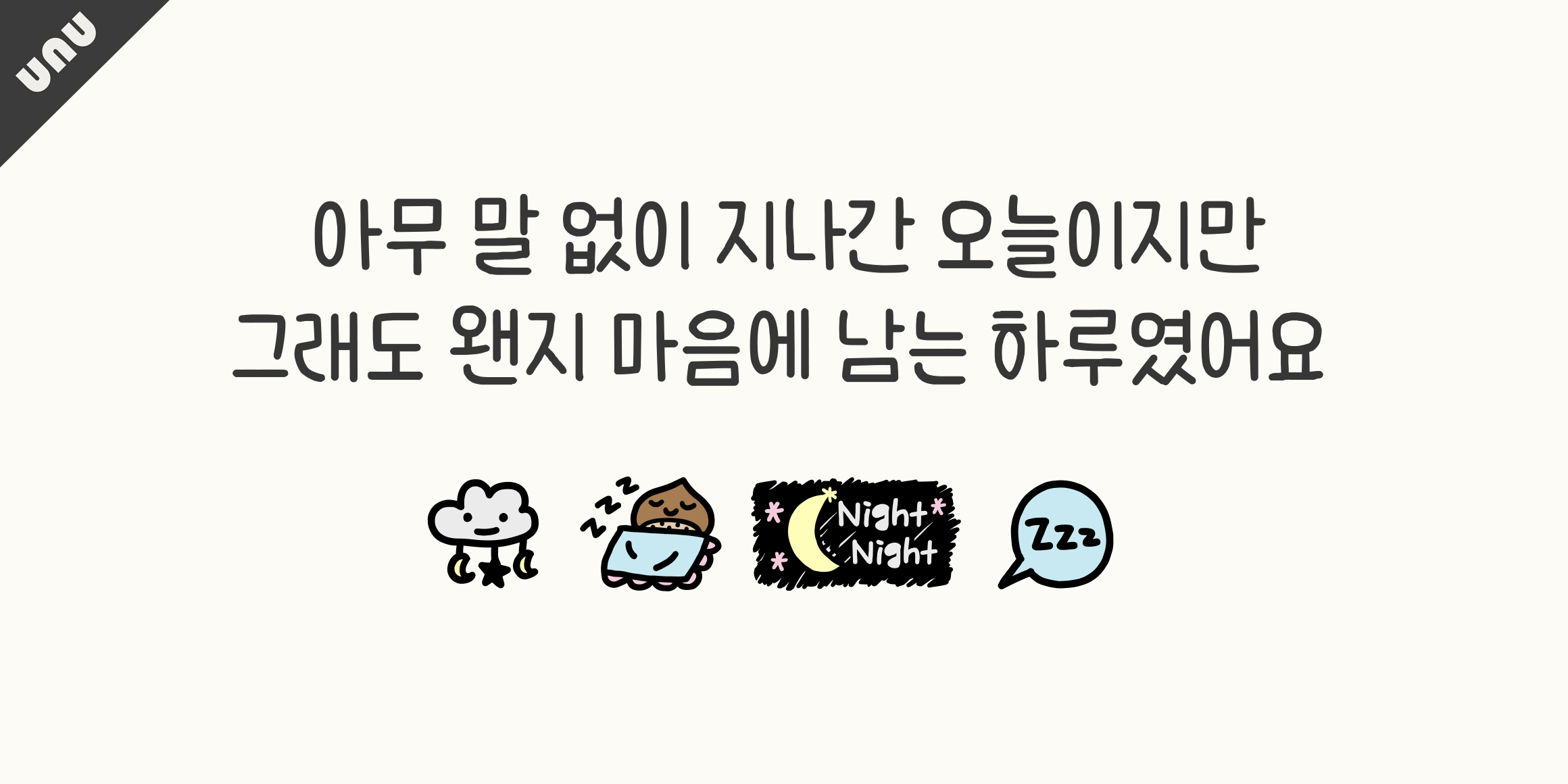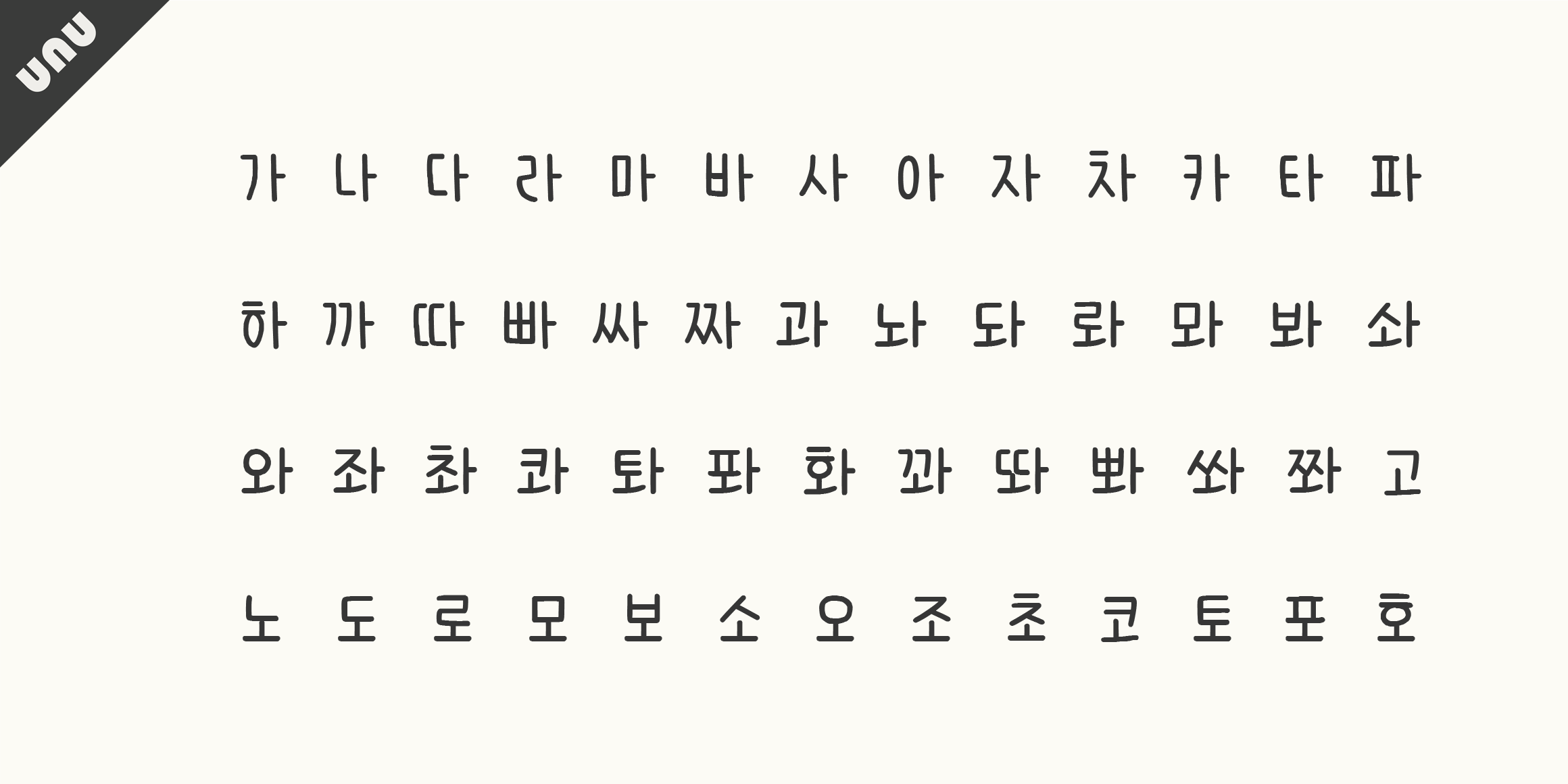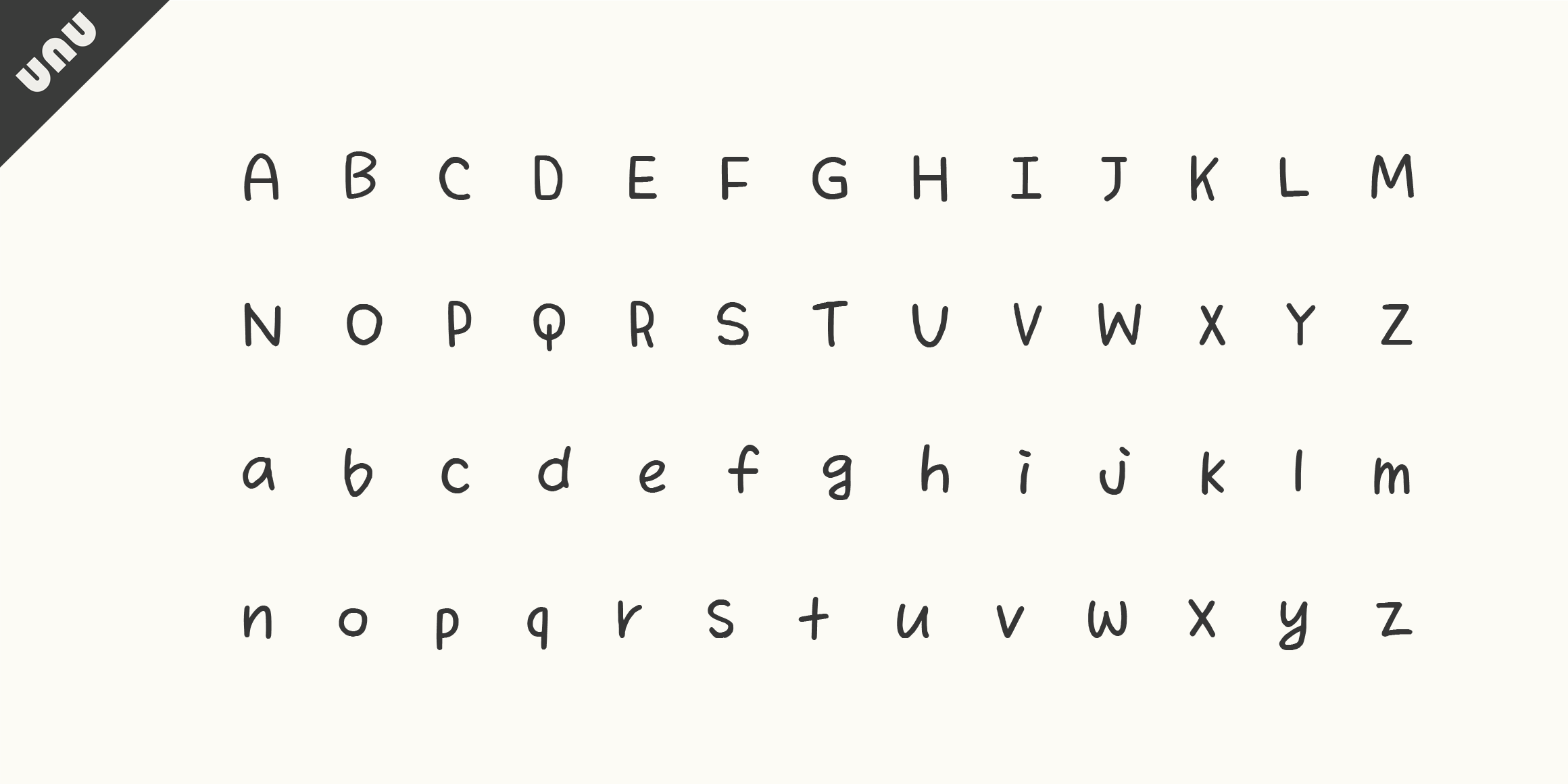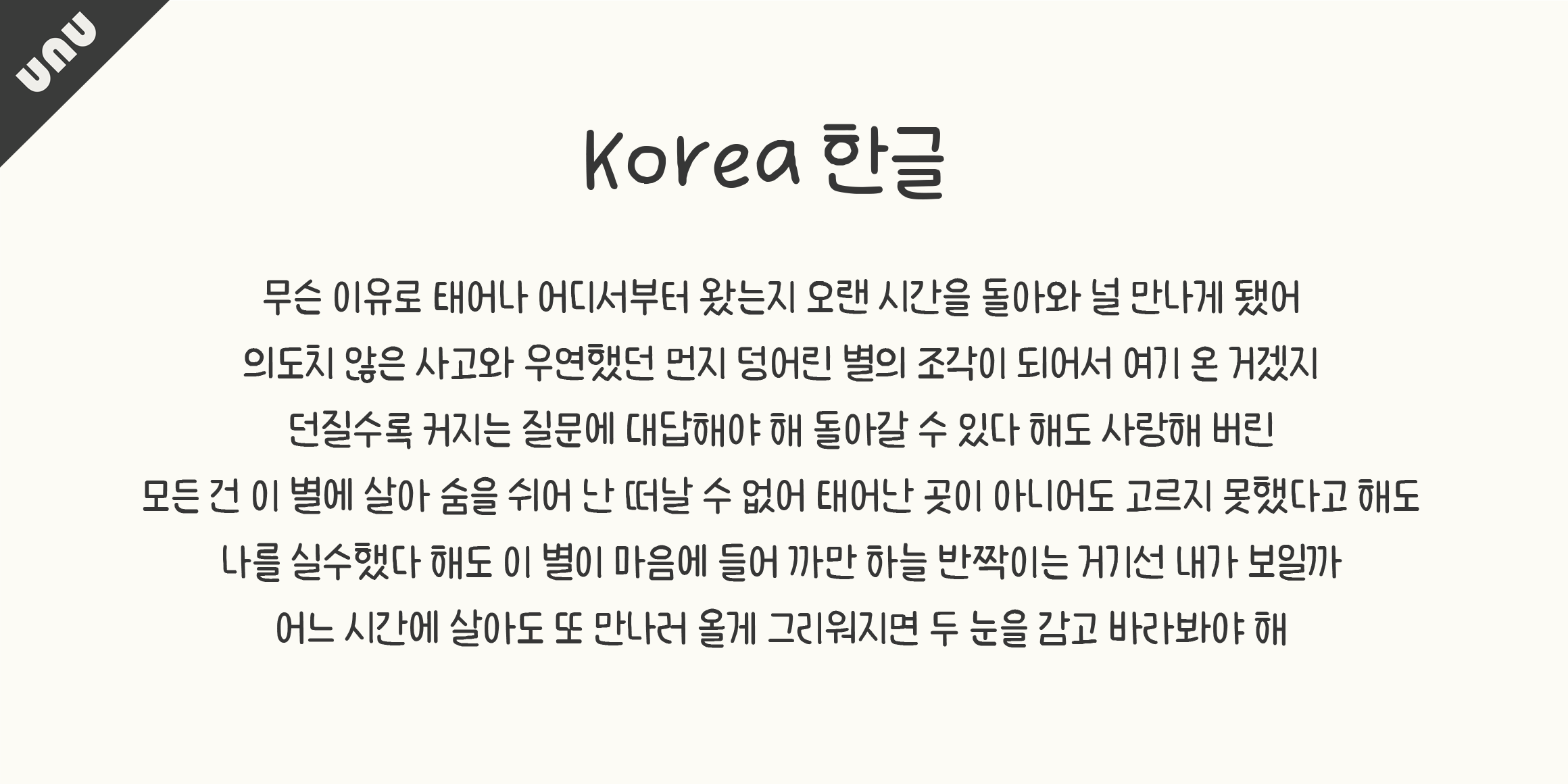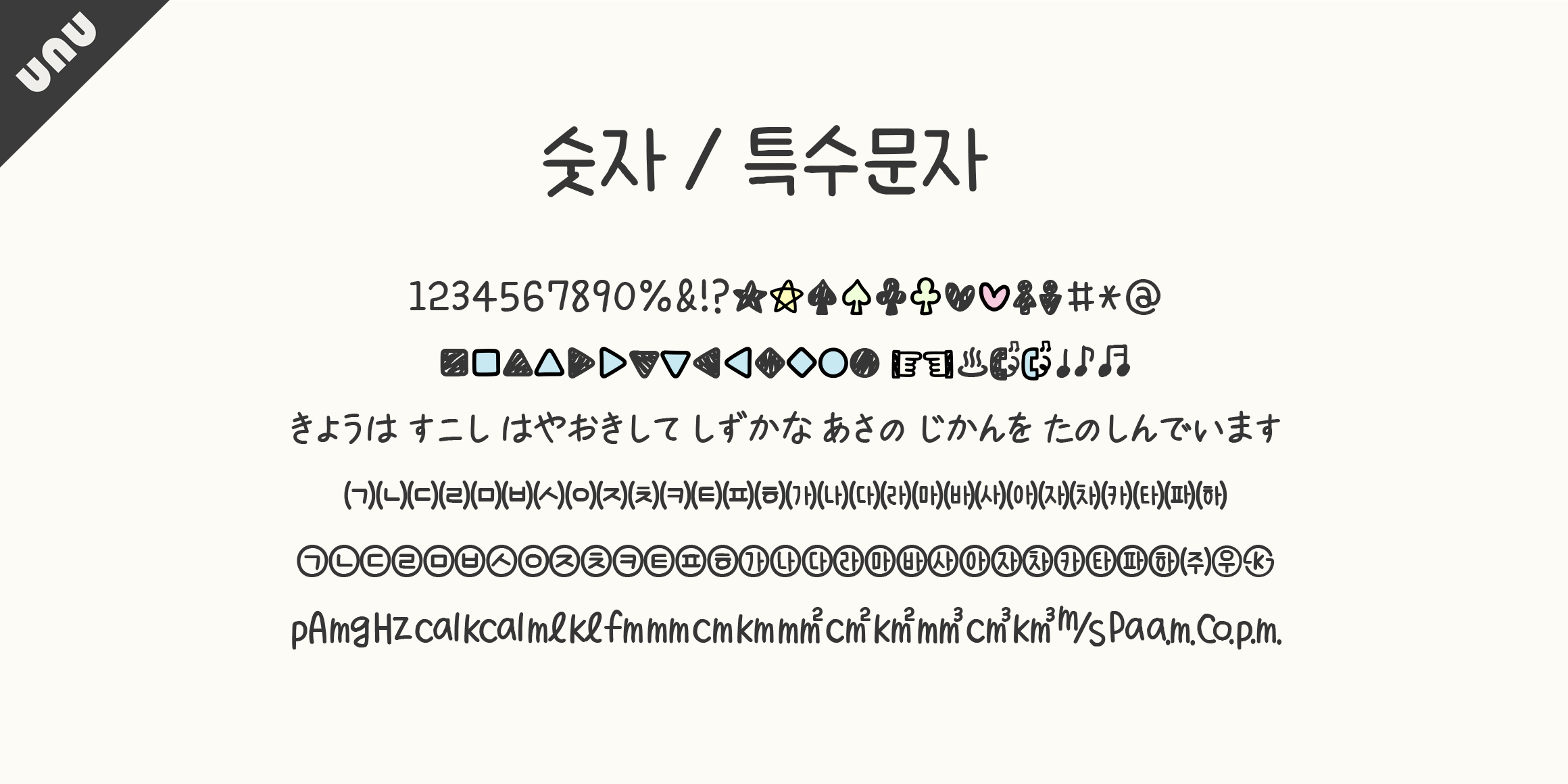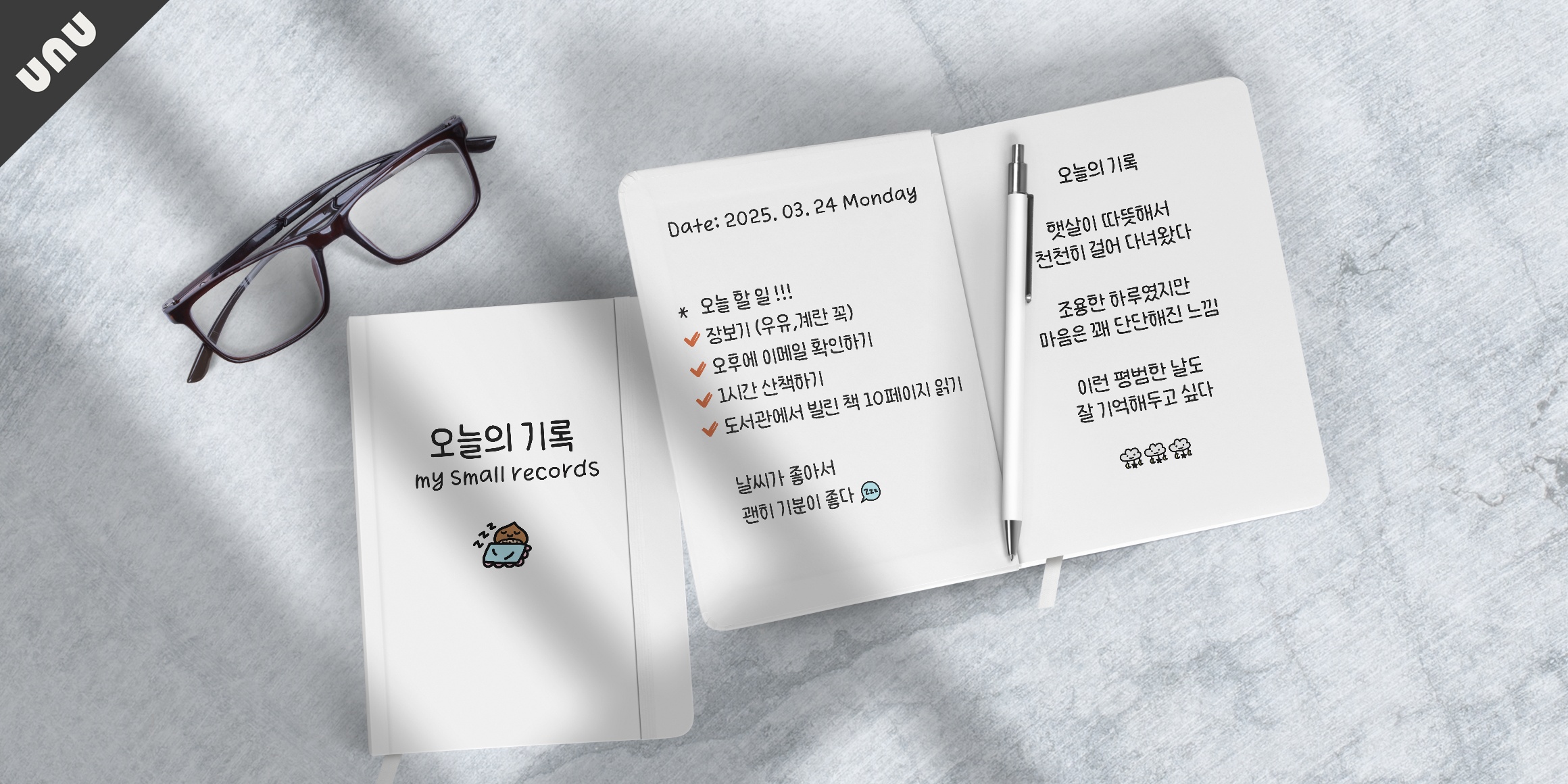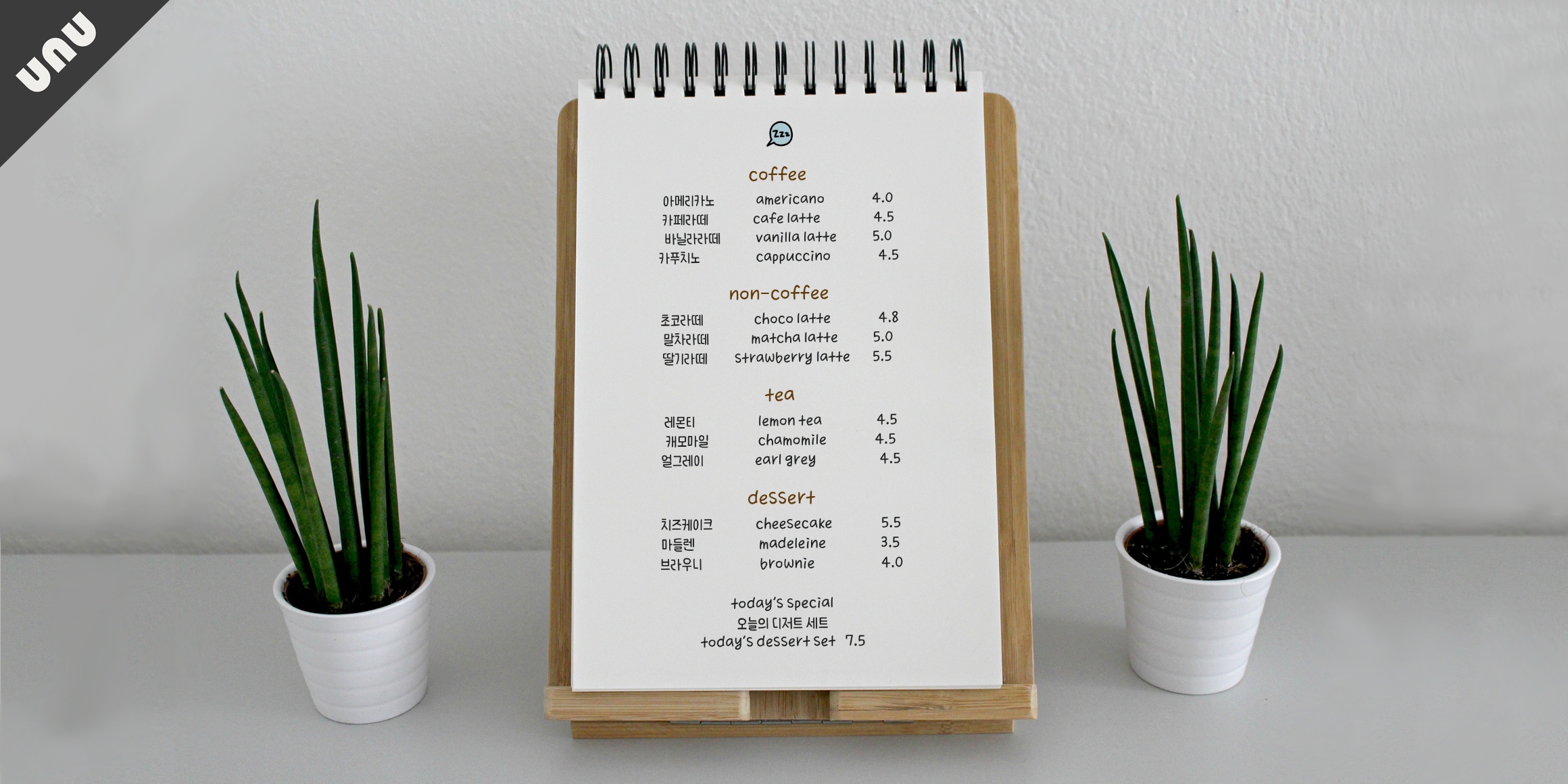
unu밤덩이
분류 Script,손글씨
이 서체는 각은 분명하지만 매끈하게 정제되기보다는 러프하고 때로는 어눌하게 흔들리는 형태를 지니고 있으며, 그 안에서 안정적인 곡선과 균형을 통해 전체적인 안정감을 유지합니다. 사랑하는 누군가에게 따뜻한 마음을 전하고 싶을때, 내 소중한 다이어리에 오늘을 기록하고 싶을때 추천드립니다. 유앤유서체는 당신의 따뜻한 마음을 전해드립니다.(컬러가 적용되지 않는 기기나 앱이 있을 수 있으며, 두껍게(Bold)처리시 두께 변화가 없을 수 있습니다.)
• Script,손글씨
• unu밤덩이 / ununightChunk